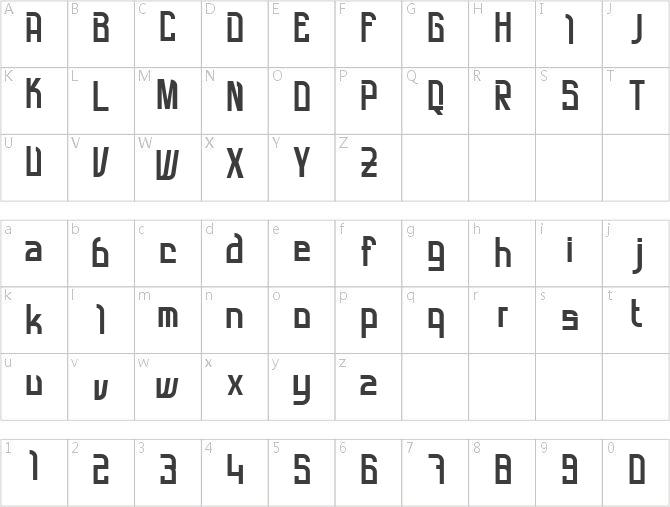
QuatSteel Update 2015
QuatSteel Update 2015介紹
QuatSteel Update 2015字體字庫是一款讓人賞心悅目、百看不厭的英文字體,適合各類廣告和產品包裝設計應用,字體大小0.03MB,格式為ttf字體,上傳用戶是373790005,作者/版權方為未知